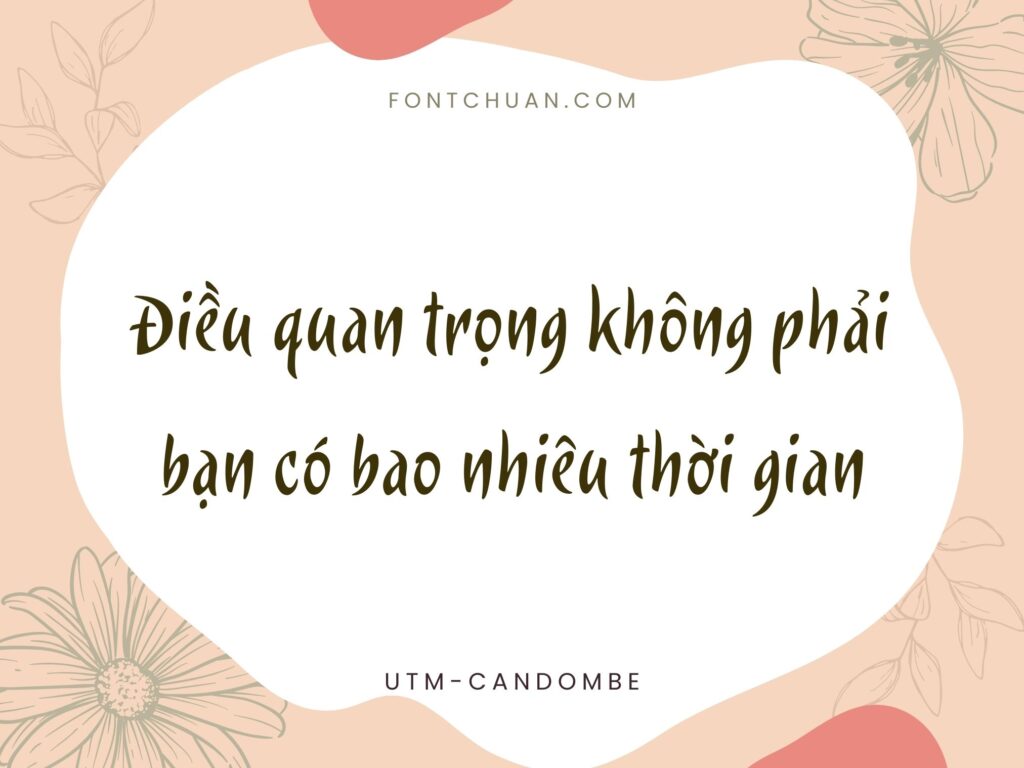
Font UTM Candombe Việt Hóa
UTM Candombe là phiên bản Việt hóa của font chữ Candombe, một kiểu chữ display mang phong cách vẽ cọ với các đường nét mạnh mẽ và năng động. Font này được thiết kế bởi Sudtipos và nổi bật với các ký tự được vẽ bằng cọ, tạo cảm giác vui nhộn và nhiệt đới. Phiên bản Việt hóa đã được thực hiện bởi Unicode Thiên Minh, hỗ trợ đầy đủ tiếng Việt cùng hơn 100 ngôn ngữ khác. Đây là một trong những font được cộng đồng thiết kế sưu tầm và chọn lọc nhằm đáp ứng nhu cầu đa dạng trong thiết kế.
UTM Candombe có cấu trúc chữ với các nét cọ dày và mỏng đan xen, tạo nên sự nổi bật và thu hút. Font này phù hợp cho các ứng dụng như thiết kế tiêu đề, logo, bao bì sản phẩm và các ấn phẩm in ấn yêu cầu sự năng động và nghệ thuật. Các ngành nghề như quảng cáo, giáo dục, công nghệ và bất động sản có thể tận dụng UTM Candombe để tạo điểm nhấn độc đáo trong thiết kế.